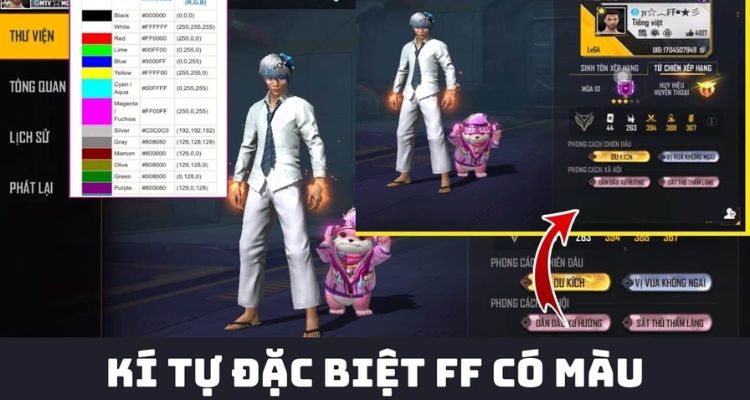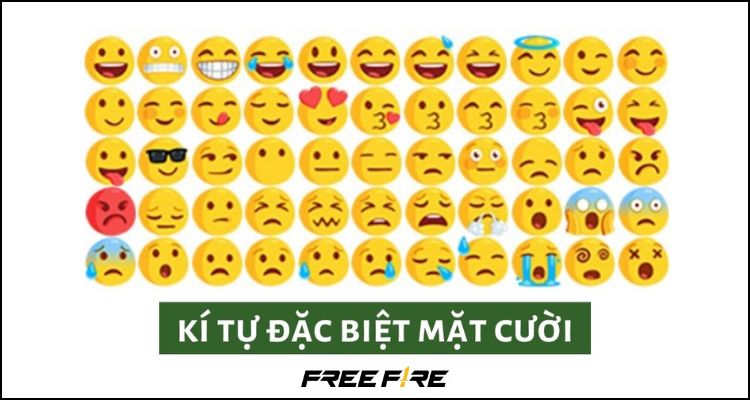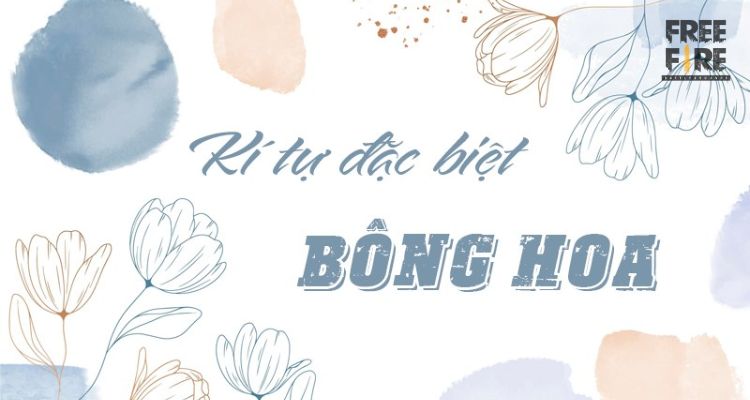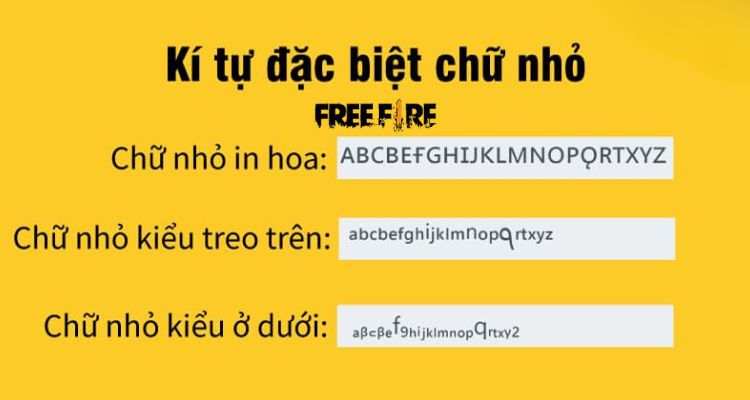
1337+ Kí tự đặc biệt FF có màu, khoảng trống, chữ nhỏ, mặt cười, bông hoa
Kí tự đặc biệt FF là những ký tự, biểu tượng, hoặc các biến thể cách điệu của chữ cái và chữ số không thuộc bảng chữ cái Latin tiêu chuẩn (A-Z, a-z) và chữ số thông thường (0-9) mà người chơi sử dụng để đặt tên nhân vật, tên Quân đoàn, sử dụng trong khung chat của game và trang trí chữ ký trong Free Fire.
Các loại kí tự đặc biệt FF thường gặp bao gồm:
Kí tự đặc biệt FF có màu sắc
Kí tự khoảng trống trong FF
Kí tự đặc biệt FF chữ nhỏ
Kí tự mặt cười FF
Ký tự bông hoa free fire
Kí tự đặc biệt FF có màu sắc là nhóm kí tự đặc biệt mang màu sắc rực rỡ đỏ, xanh, vàng,.. nổi bật và thường được dùng để trang trí tên nhân vật trong game Free Fire như ❤️ (U+2764) và 🌈 (U+1F308). Tham khảo bộ sưu tập những biểu tượng độc đáo và được nhiều game thủ yêu thích sau đây:
Kí tự đặc biệt FF khoảng trống có mã Unicode như Zero Width Non-Joiner (U+200C), Zero Width Joiner (U+200D) là nhòm kí tự đóng vai trò quan trọng, giúp người chơi FF tạo ra tên nhân vật độc đáo, dễ đọc và ấn tượng hơn. Dưới đây là các kí tự khoảng trống FF dành cho bạn:
Tên FF kí tự đặc biệt chữ nhỏ là các chữ cái được hiển thị với kích thước nhỏ hơn so với chữ thường thông thường, chúng đang trở thành xu hướng được nhiều game thủ lựa chọn để làm mới nhân vật của mình. Dưới đây là gợi ý về các ký tự đặc biệt FF chữ nhỏ đẹp, dễ sử dụng: